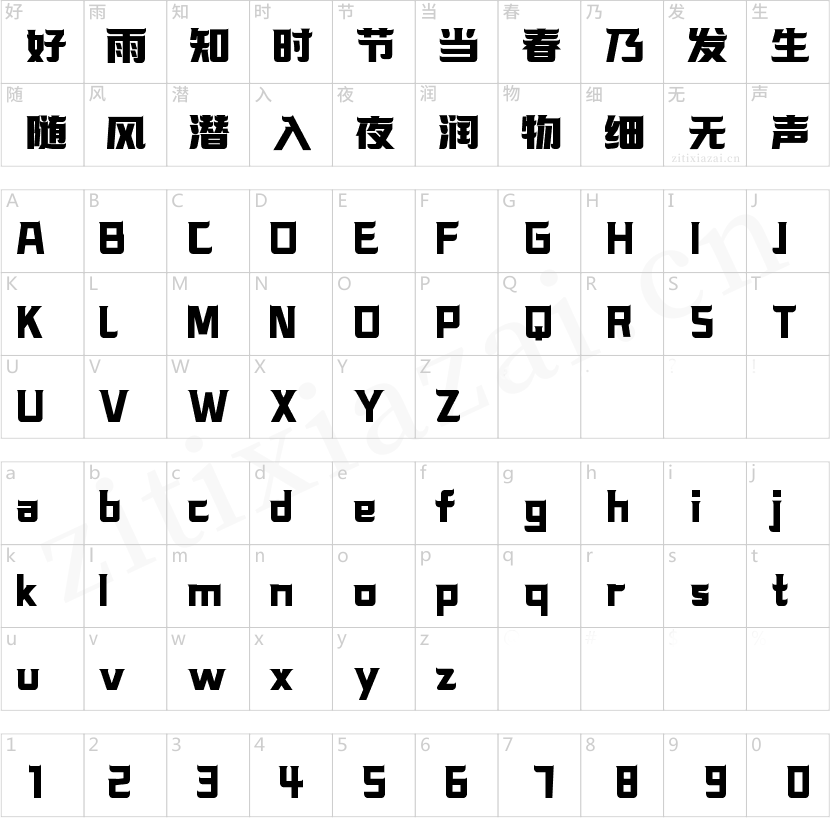
字魂秘境黑
字魂秘境黑,这款字体结构工整、笔画清晰,兼顾美观与易读性,适用于标题、正文、海报、包装、LOGO 等多种场景。字形优雅稳定,风格百搭耐看,适配日常排版与创意设计,让文字呈现更舒适、更具质感。字魂秘境黑一笔一画,皆是细节,以均衡的比例、流畅的线条打造舒适视觉体验,字形端正大气,风格简约现代。无论是商业设计、品牌宣传还是日常排版,都能轻松驾驭,让文字更有格调与力量。字魂秘境黑字体下载。
字魂字体字魂秘境黑字体是由字魂创意字库设计并生产的一款可商用的字体,被收录于字魂先锋系列。该字体支持GB-2312标准,包含6763个中文、字母、符号和数字,字体类型偏向黑体,具有力量、时尚的风格,在市面上广泛用于母婴、标题字、旅游等场景。